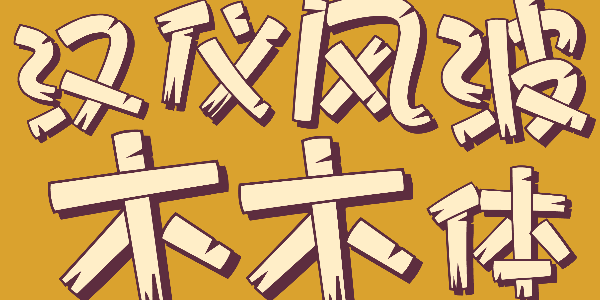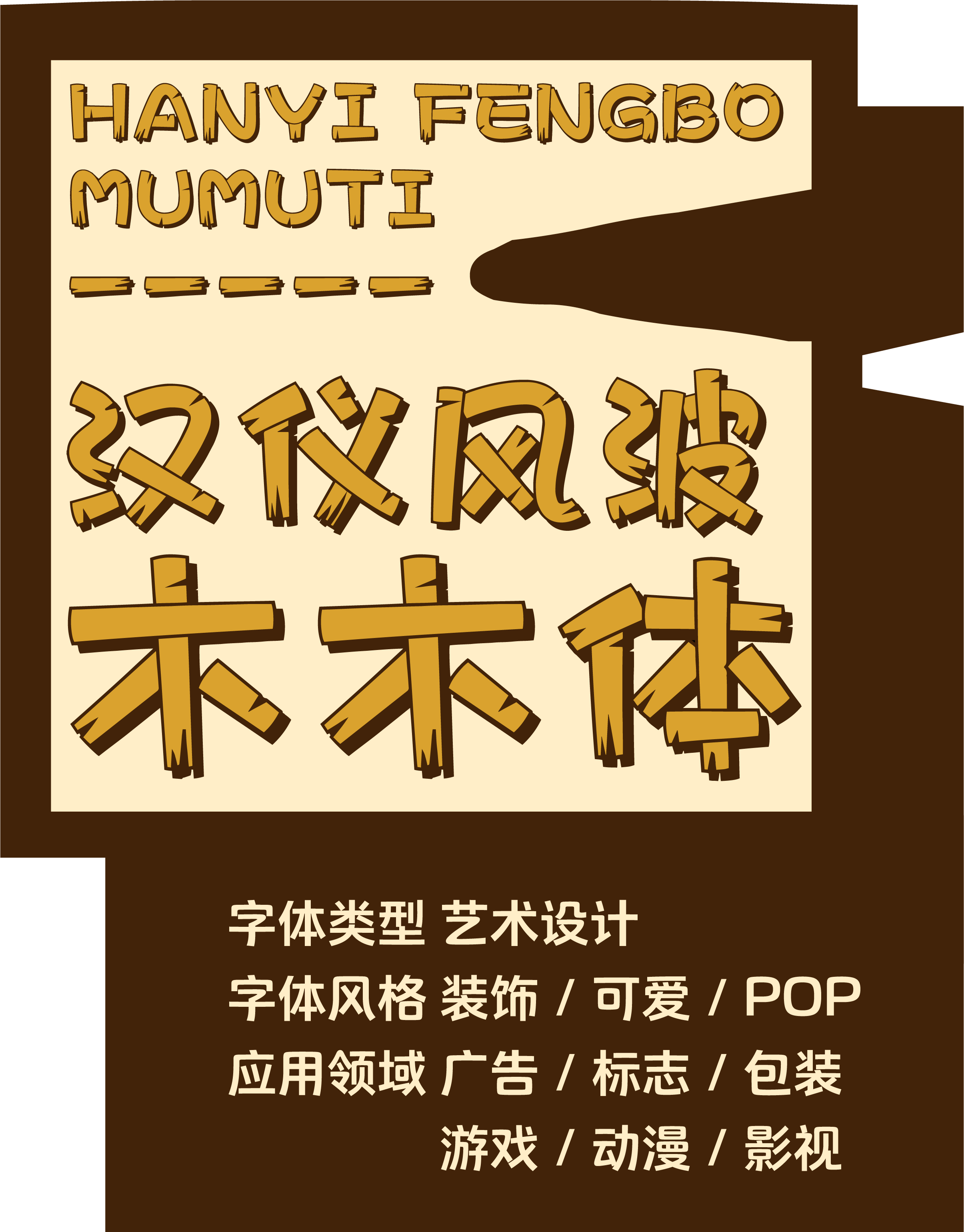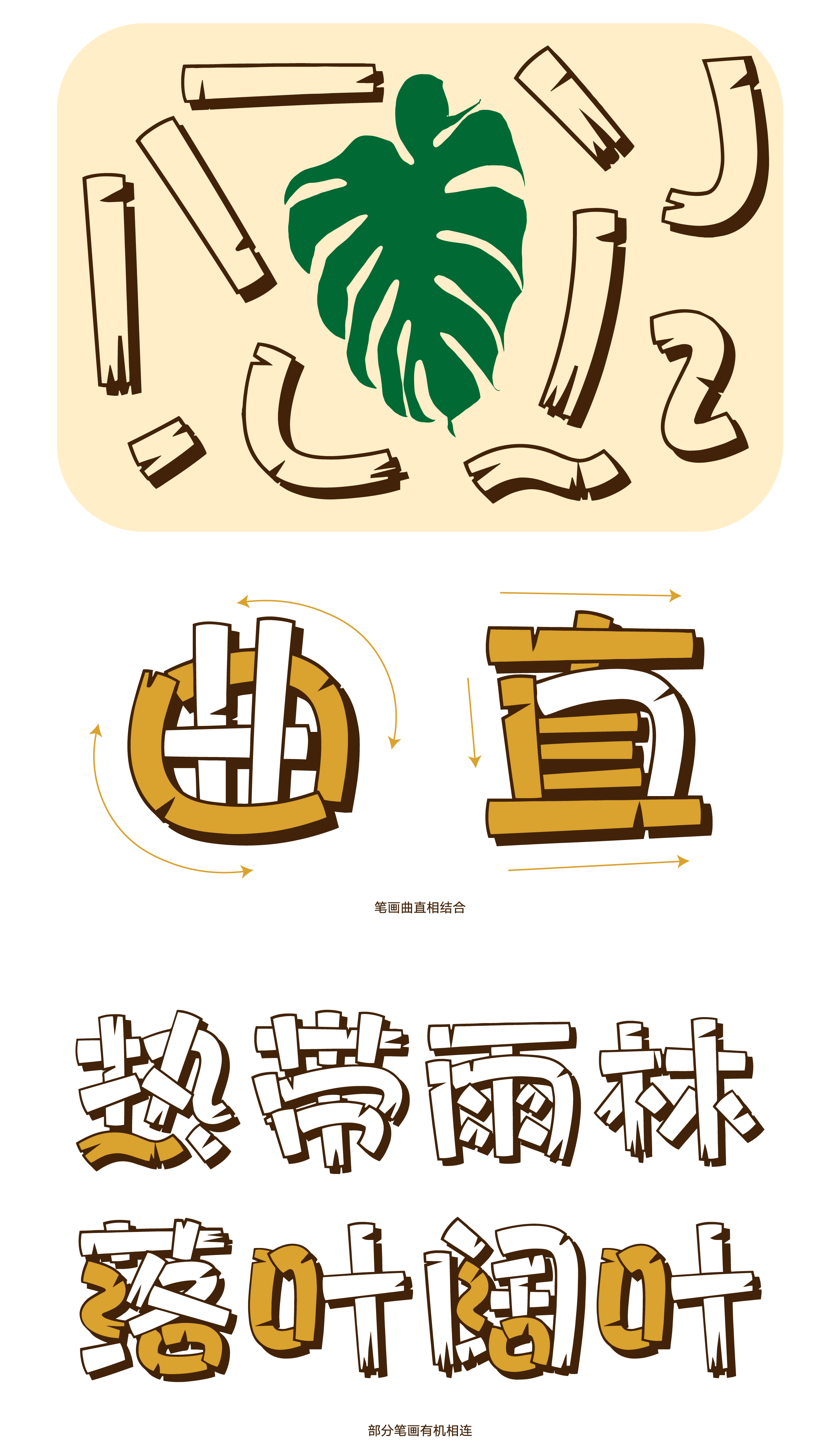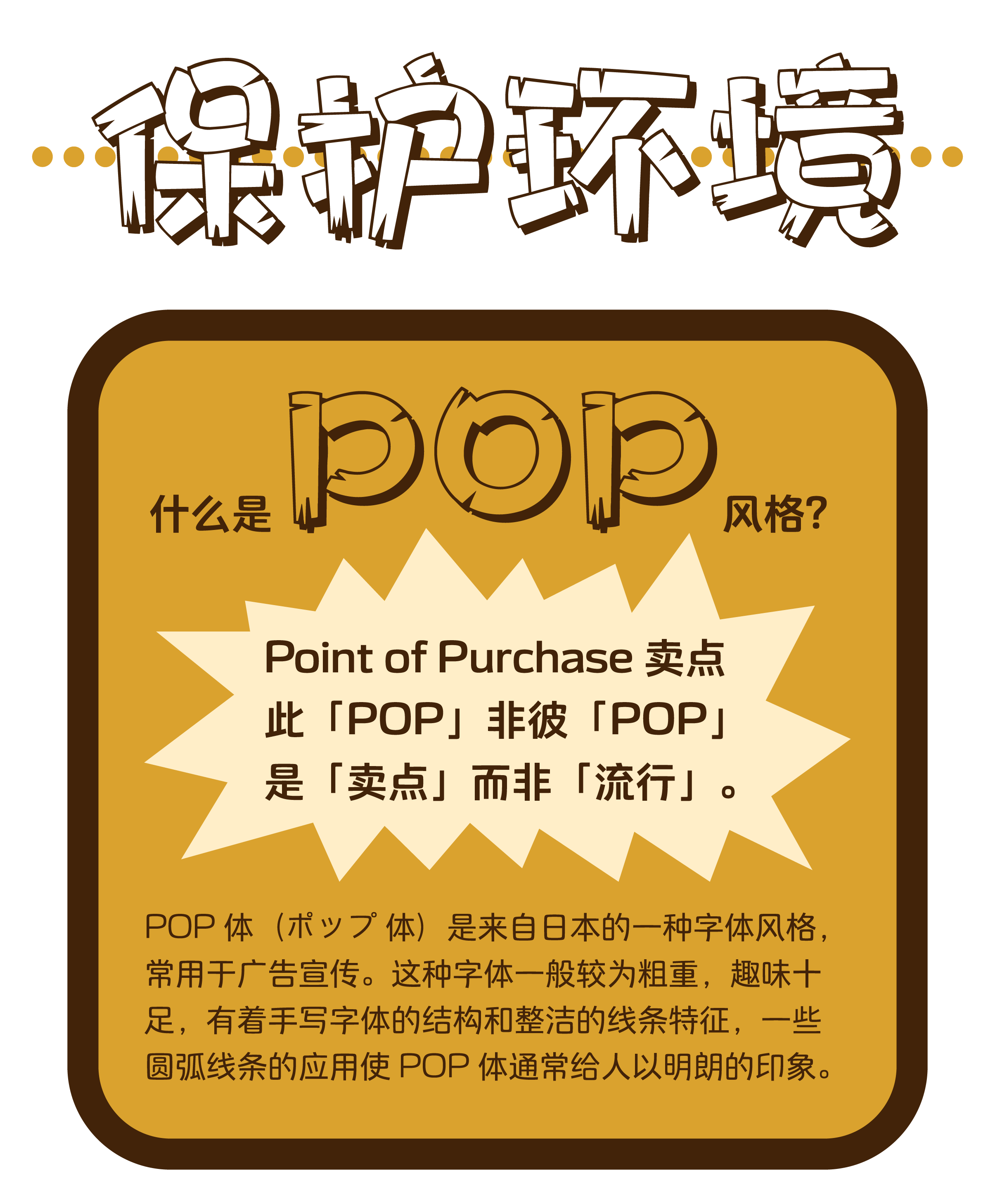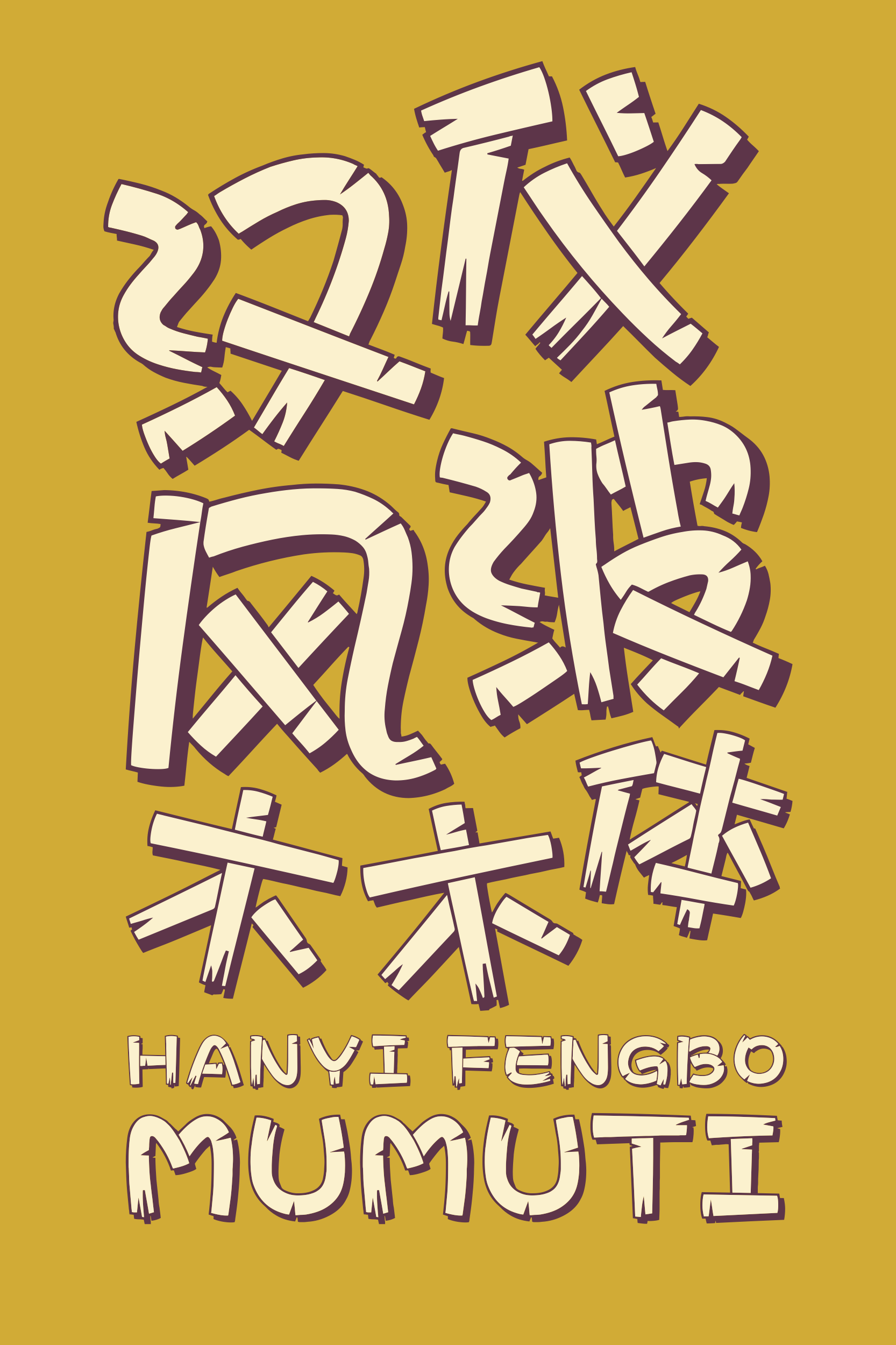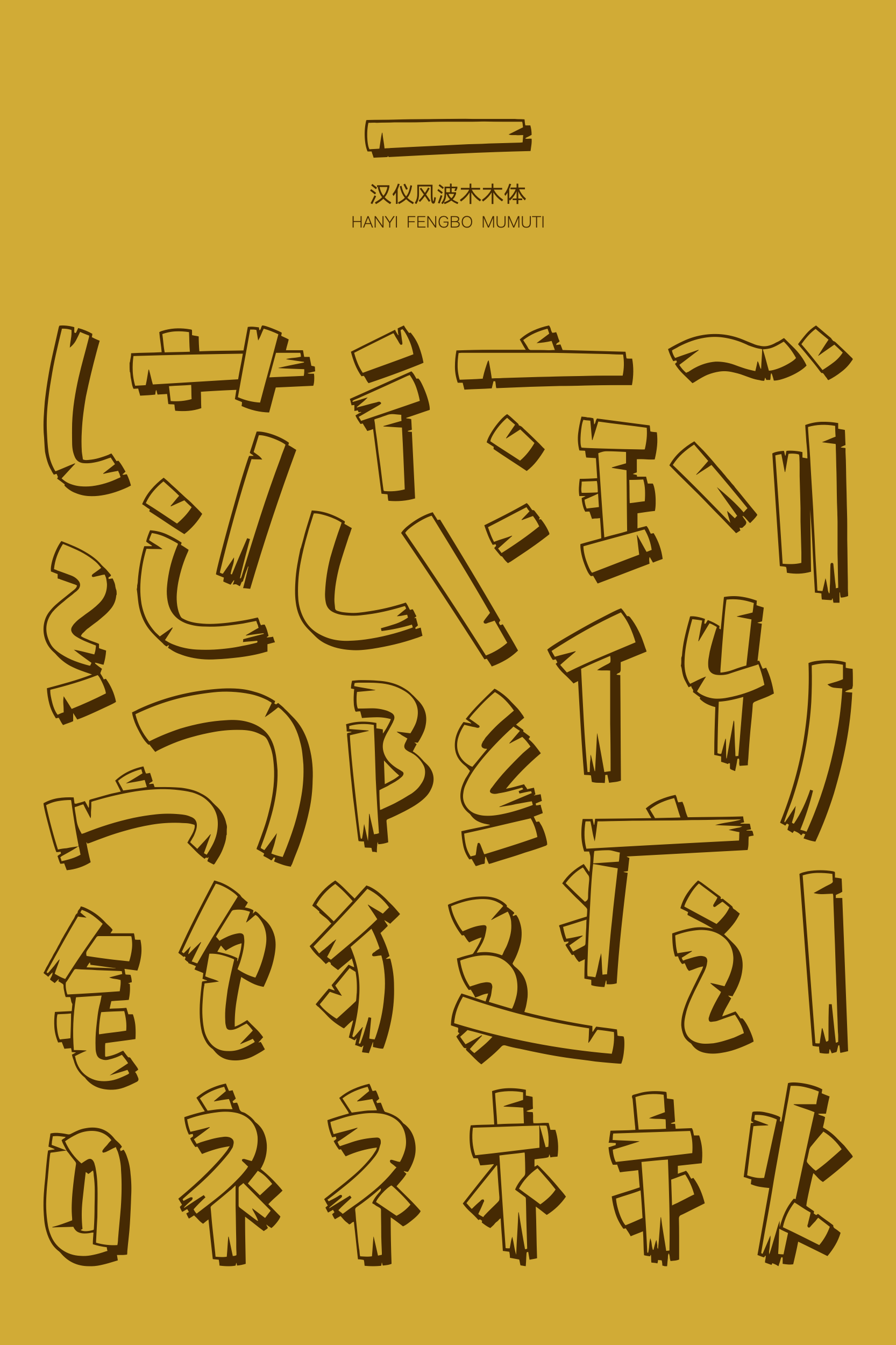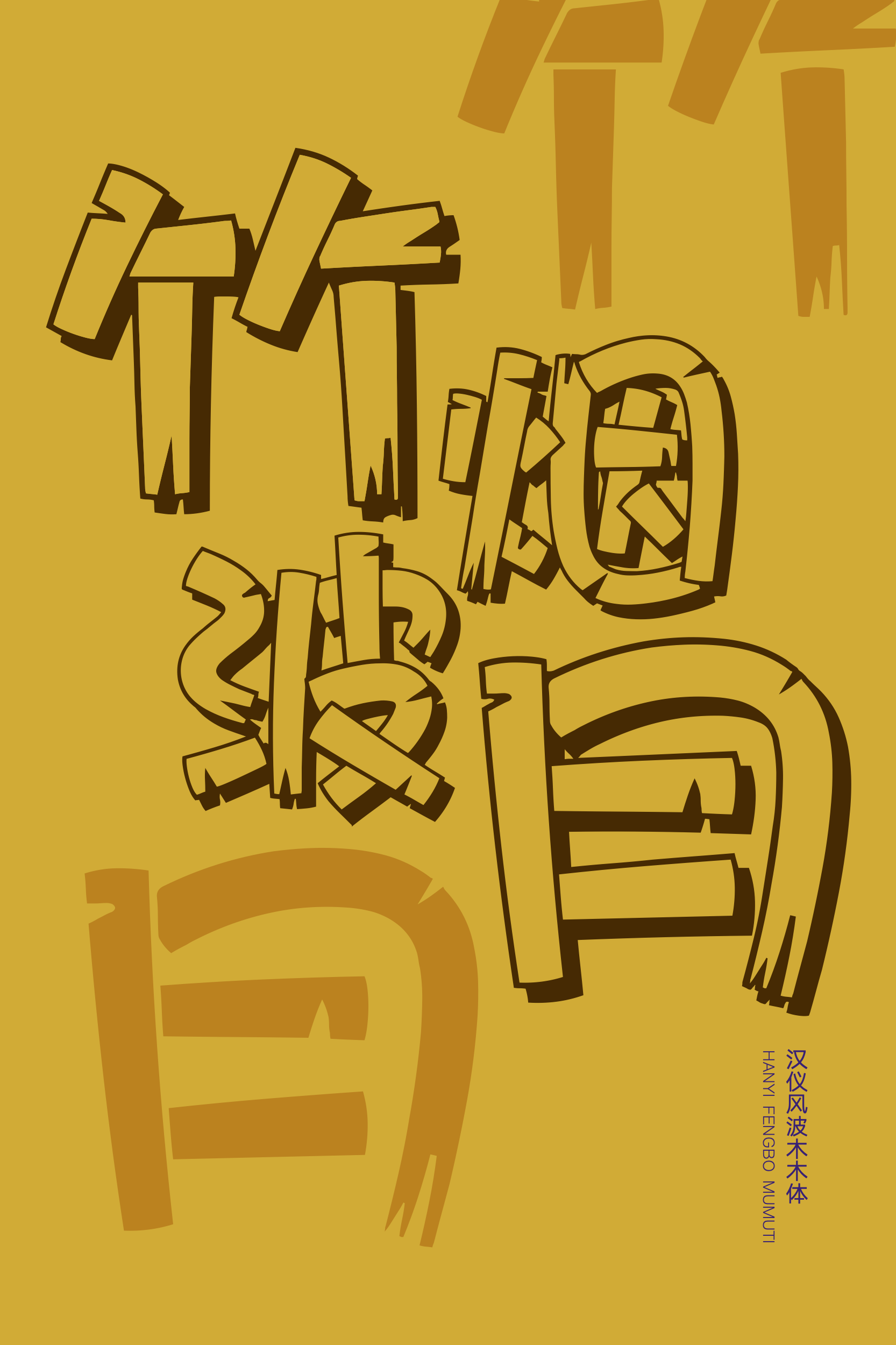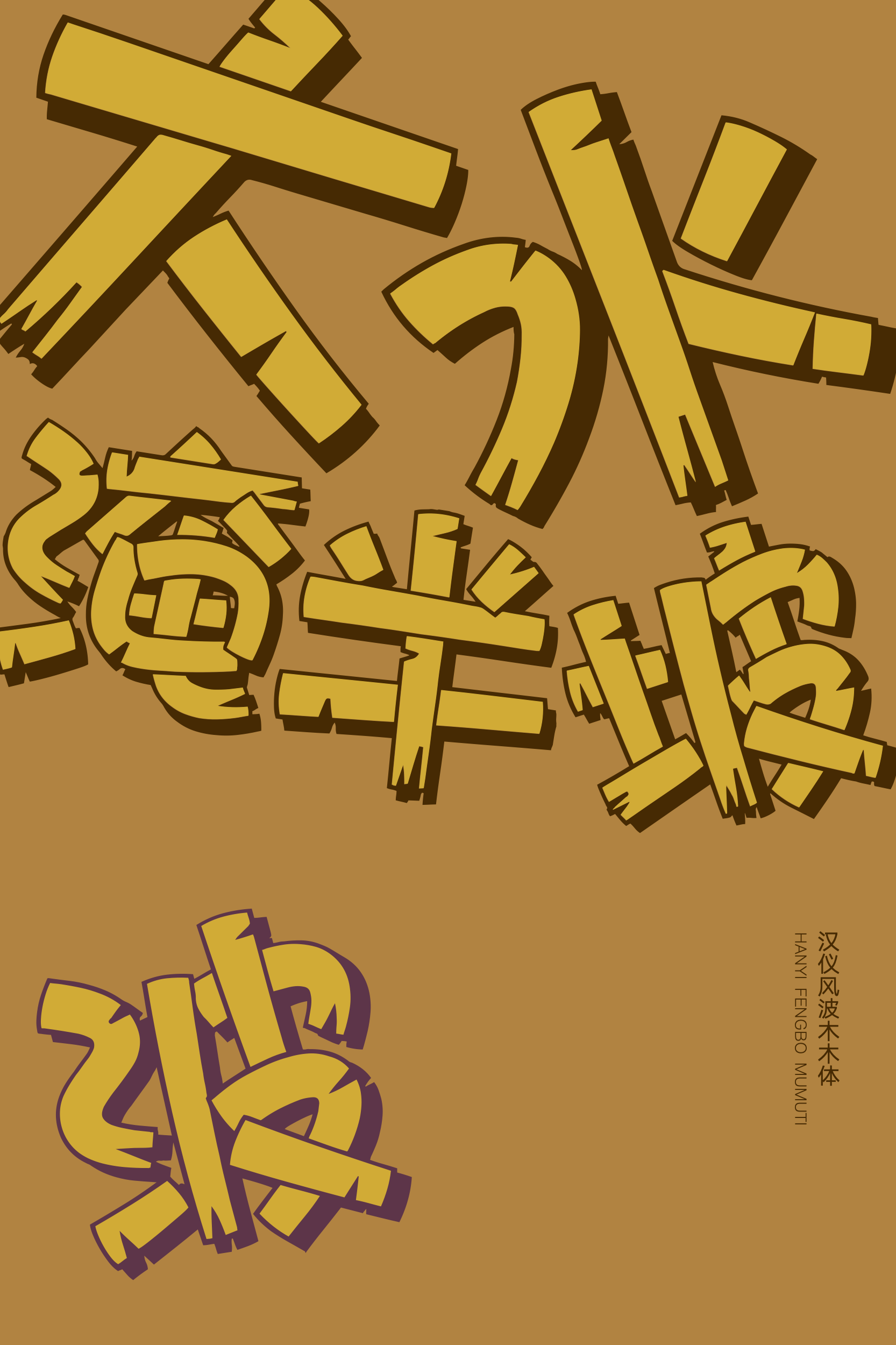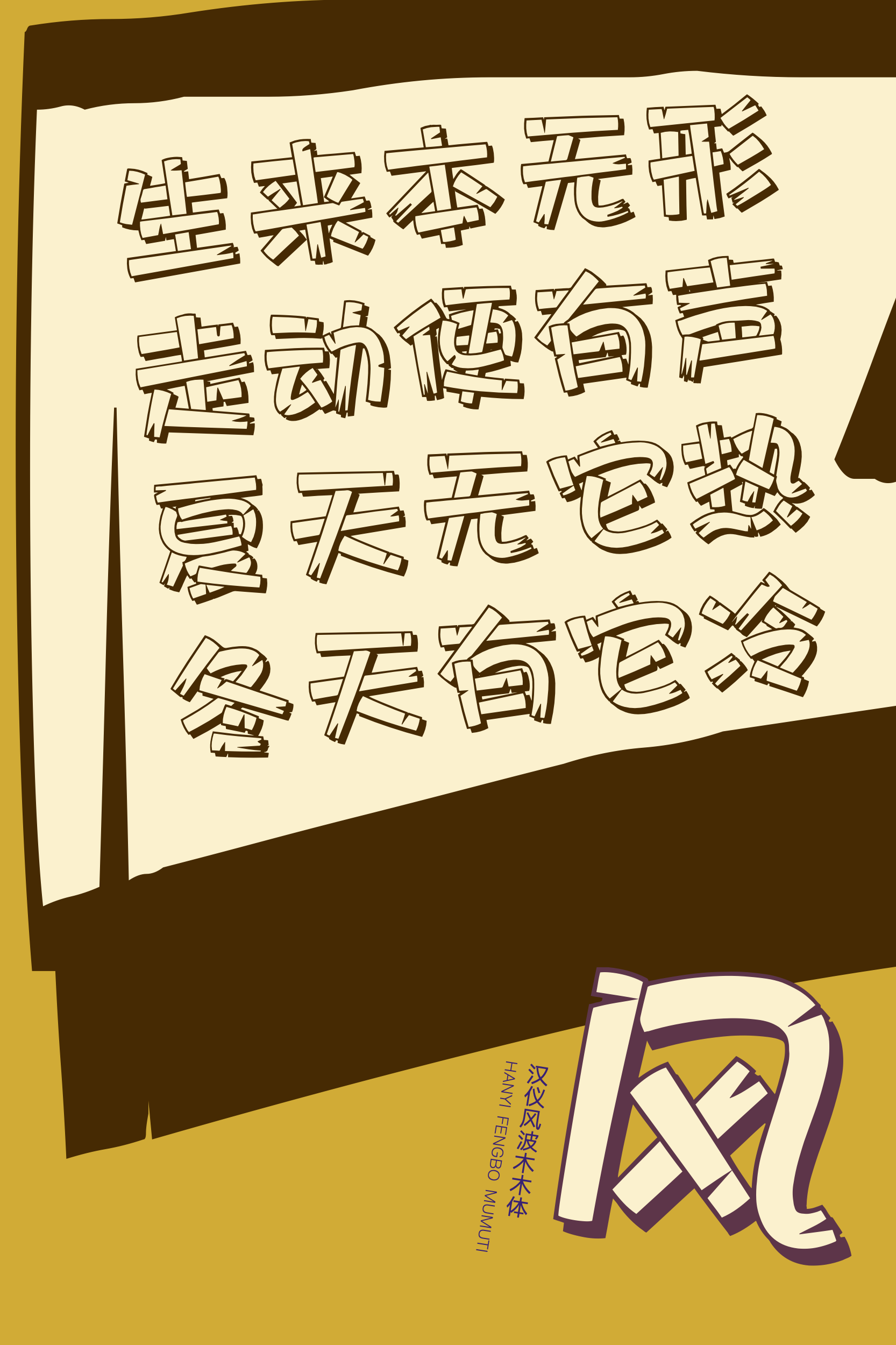
用字体搭一座小木屋
汉仪风波木木体由汉仪字库签约设计师梁风波创作,是一款趣味横生、可爱活泼的 POP 风格的镂空字体。字形饱满,笔画堆叠,加上镂空设计与阴影的搭配,整体有着突出的立体感和视觉表现力。这款字体适合作为标题字体应用于各类欢乐休闲的使用场景,色彩搭配和材质应用的灵活可能性也许会让汉仪风波木木体给你带来意想不到的惊喜效果!
字形结构采用了活泼有趣的 POP 风格,字形饱满,重心略低。
汉仪风波木木体的灵感来源于热带雨林中茂密的阔叶类植物,将叶片长阔开裂又富有生命力的特点融入笔画的设计,有曲有直,部分笔画有机相连。
镂空与阴影的搭配带来突出的视觉表现力。
笔画堆叠穿插,不仅立体感加倍,更添生动趣味。
汉仪木木体的西文部分的上升部和下降部较小,视觉集中于字形中部的 x 字高,显得饱满,与中文部分充实的字形相匹配。